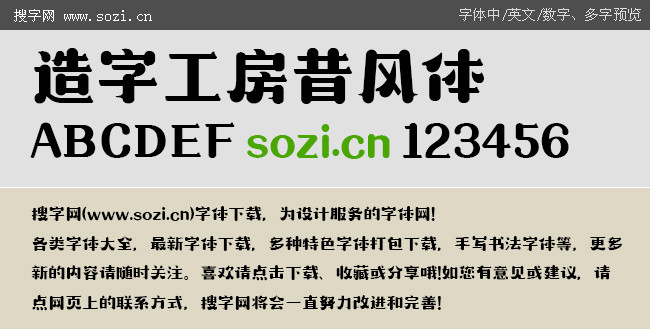
造字工房昔風(fēng)體
搜字網(wǎng)給大家提供一款造字工房昔風(fēng)體中文字體下載,造字工房昔風(fēng)體風(fēng)格遒勁潤(rùn)雅,結(jié)構(gòu)隨性自由,筆勢(shì)恍如飛鴻戲海,結(jié)體嚴(yán)緊,筆畫穿插緊密、粗勁圓潤(rùn)、渾厚寬博,令其筆力恬潤(rùn)、婉暢又不失端正。適用于海報(bào)設(shè)計(jì),網(wǎng)頁(yè)廣告,書籍封面,包裝設(shè)計(jì)等應(yīng)用。(本字體為個(gè)人非商用版,如需要商用請(qǐng)聯(lián)系官方購(gòu)買版權(quán))